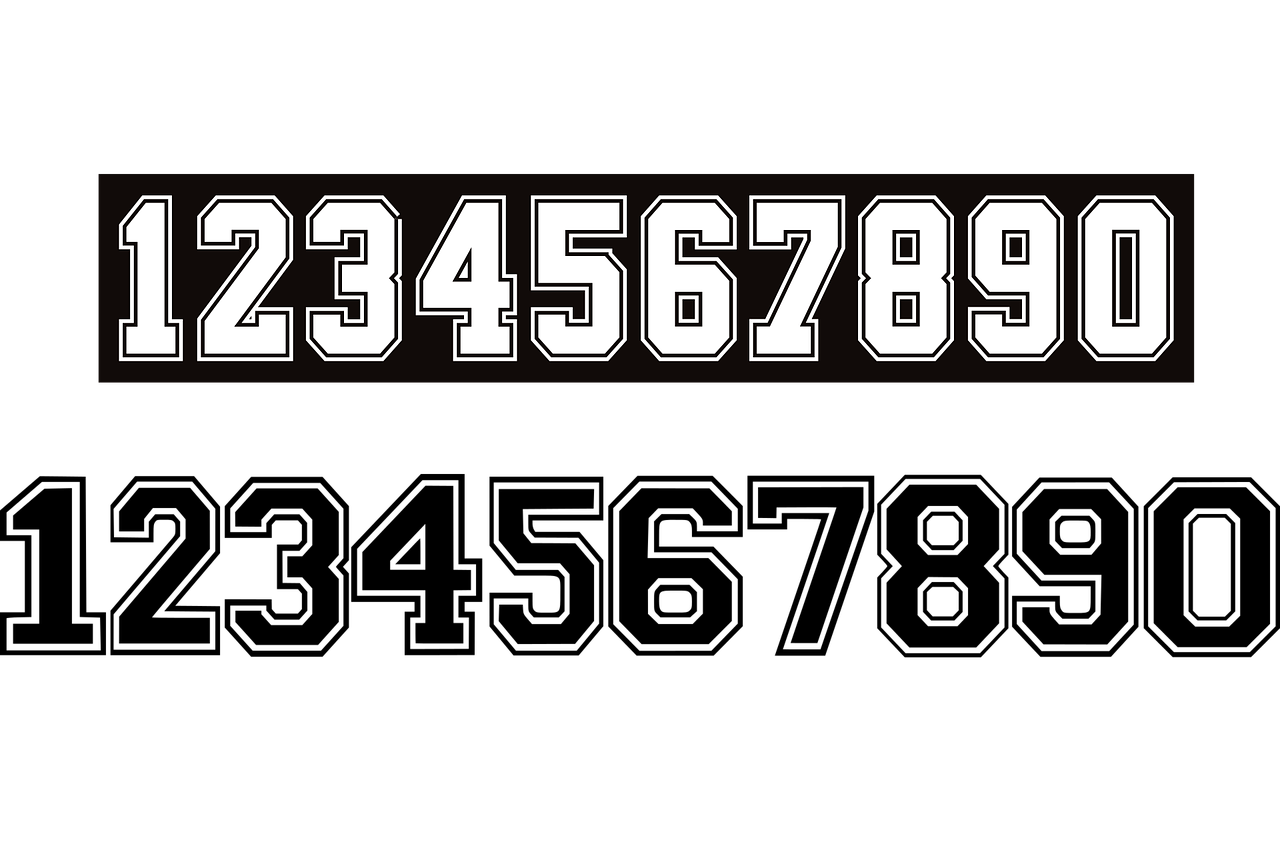
ТОП-10 БЕСПЛАТНЫХ ШРИФТОВ ADOBE ДЛЯ СПОРТИВНЫХ ДИЗАЙНЕРОВ — UniMockups.com
Если вы увлекаетесь спортивным дизайном, вы, вероятно, потратили бессчетное количество часов на поиск идеального шрифта для данного дизайна. У вас, вероятно, также есть несколько шрифтов, которые вы предпочитаете для графики партитур, унифицированных чисел или любого другого приложения, о котором вы только можете подумать. Потратив некоторое время на Adobe Fonts, я решил составить список из 10 лучших бесплатных шрифтов Adobe для спортивных дизайнеров с оговоркой, что они бесплатны* для использования подписчиками Adobe.
Очень универсальный шрифт с большим количеством жирных шрифтов и вариантов курсива, Mongoose был принят в качестве «официального» шрифта UniMockups и включен в веб-сайт. Mongoose похож, если не на точный шрифт, на шрифты, используемые многими профессиональными спортивными организациями на протяжении многих лет, включая НБА.
Другой популярный шрифт в профессиональных спортивных организациях, Aktiv Grotesk, опять же имеет множество вариантов жирности и курсива. Жирные варианты этого шрифта — отличный выбор для графики, которой нужны привлекательные заголовки, оценки, статистика или что-то еще, что нужно выделить, в то время как более светлые варианты отлично подходят для подтекста.
Используемый Adobe, Myriad — это очень элегантный шрифт с множеством опций, позволяющих выделить ваш текст. Я видел этот шрифт, используемый многими дизайнерами для различных презентаций. Это хороший выбор для четкой удобочитаемости.
Industry Inc предлагает широкий спектр опций, которые могут быть полезны в различных спортивных приложениях. Базовый шрифт очень чистый и жирный, но есть также скошенный, контурный, встроенный, трафаретный и другие варианты для максимальной универсальности.
Я люблю Сухой закон, особенно набор цифр. Для меня Prohibition сильнее таких шрифтов, как Varsity Block.
Brothers — отличный шрифт для винтажного образа, как видно на примере изображения выше с текстом New York Knickerbockers. Это супер-уникальный шрифт, который можно использовать различными способами, чтобы добавить характер любому дизайну. У Brothers также есть интересный набор чисел, который отлично смотрится в правильном контексте, но я обнаружил, что они слишком широкие для моего дизайна униформы.
Carbon поставляется с множеством вариантов веса и курсива, но лучшая часть набора номеров. Я много раз использовал этот шрифт в шаблонах UniMockups для текста на тегах спортсменов. Я видел набор чисел, используемый несколькими профессиональными спортивными организациями для графики статистики.
Да, заезжено — но на то есть причина. Futura просто выглядит хорошо большую часть времени. Он чрезвычайно универсален, и «Питтсбург Стилерс» использует его для своих форменных номеров.
Dimensions — это сверхсжатый шрифт с различной насыщенностью. Мне очень нравится этот шрифт за добавление блочных фрагментов текста с очень отчетливым внешним видом. Измерения отлично подходят для добавления текстуры и 3D-отделки.
Вообще-то есть такая версия под названием Octin Sports, но мне она не очень нравится. Это еще один шрифт, похожий на Varsity Block и Prohibition, который отлично подходит для спортивных приложений.
Дизайнеры даже использовали стадион на одном из примеров изображений, как показано выше.
Какие ваши любимые шрифты для спортивного дизайна или вообще? Оставьте нам комментарий ниже.
30+ лучших спортивных шрифтов (для брендинга, логотипов и многого другого!)
Если вы ищете лучших спортивных шрифтов , эта функция для вас!
Как и многие категории шрифтов, спортивные шрифты являются одними из самых прибыльных онлайн-активов. Мало того, что спортивное сообщество процветает, это еще и многомиллиардная индустрия. А какой прибыльный бизнес без соответствующих дизайнов?
От школьных плакатов до профессиональных спортивных команд, все представленные ниже спортивные шрифты являются одними из самых популярных наборов шрифтов ниже!
- Houston Sports Font Family
- BALLOCS TEXTURED SPORT FONT
- New Sport Font
- Rodwick- Шрифт Classic Sport
- Freekick — шрифт Sport Display
- Hillary — A Sport Display Шрифт
- Шрифт Gymer Sport
- Mandala – Display Sport Font
- Devgon Vintage sports display font
- Darknight
Чтобы просмотреть полный список, пролистайте дальше!
Также смотрите наши публикации о лучших шрифтах для киберспорта, лучших шрифтах для бейсбола, лучших шрифтах для джерси и лучших шрифтах для тренажерного зала для схожей эстетики.
Какой спортивный шрифт подходит для футуристического и научно-фантастического дизайна?
Quicker — это спортивный шрифт, который легко можно использовать в качестве галактического шрифта. Подходит для дизайна онлайн-игр и проектов одежды, эта деталь имеет закругленные углы.
Есть ли отличные узкие спортивные шрифты с засечками?
Helofone — отличный узкий спортивный шрифт с засечками, который имеет углы с острыми краями.